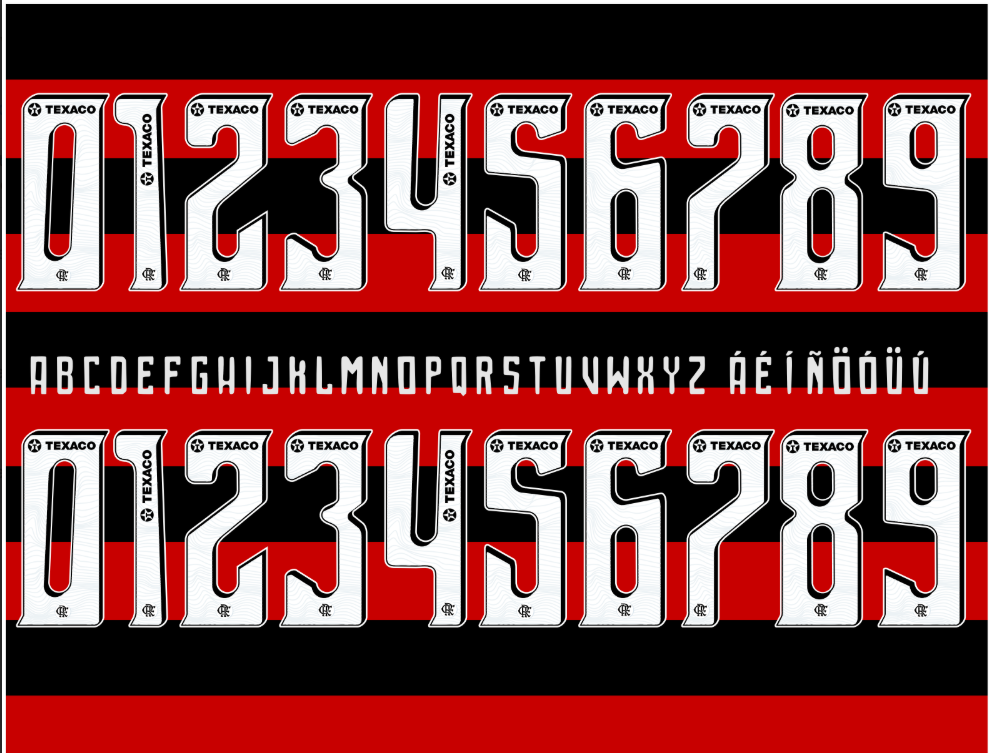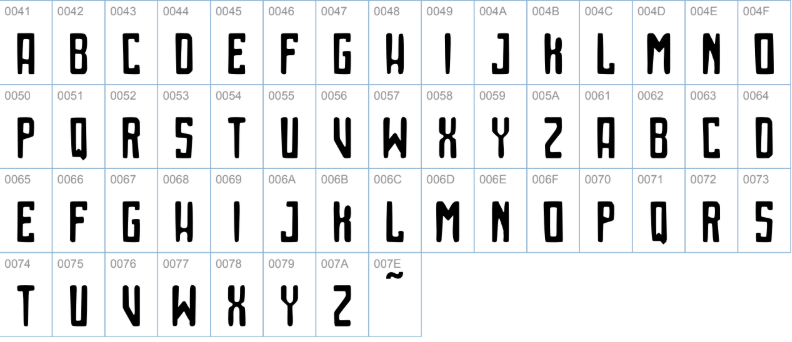
A Nação Rubro-Negra é movida por uma paixão que transcende o campo, e essa paixão está em cada detalhe do “Manto Sagrado”. Para a temporada 2025, a Adidas desenvolveu a nova identidade visual do Clube de Regatas do Flamengo, e um dos elementos centrais é a tipografia (fonte) exclusiva usada nos números e nomes dos jogadores.
Esta é a fonte que estampa as costas dos craques no Maracanã, na Libertadores e em todas as batalhas do ano. Para designers, profissionais de personalização (sublimação) ou torcedores que desejam criar artes autênticas, usar a fonte correta faz toda a diferença.
Detalhes Técnicos da Fonte
- Nome: Flamengo 2025 (Tipografia oficial Adidas)
Análise do Estilo Visual
A fonte do Flamengo para 2025 é moderna, arrojada e desenhada para impacto. Ela possui linhas fortes e um design levemente angular, transmitindo energia e velocidade, características do DNA ofensivo do time.
É uma fonte sans-serif (sem serifa) robusta, que garante máxima legibilidade tanto nas transmissões de TV quanto à distância, no estádio. A Adidas utiliza esta tipografia em todos os uniformes de jogo da temporada: o tradicional Rubro-Negro (Home), o branco (Away) e os uniformes alternativos ou de goleiro.